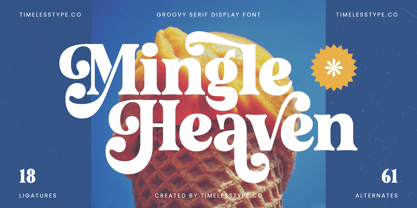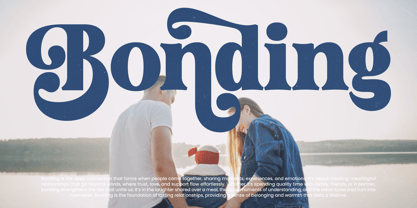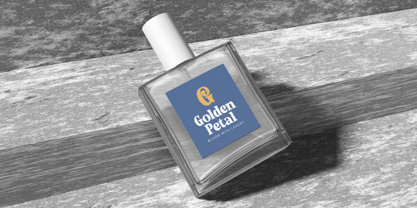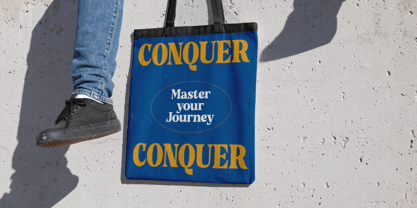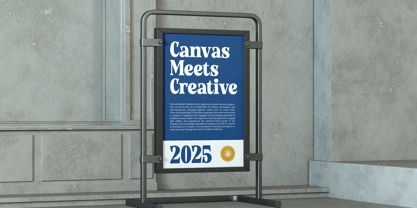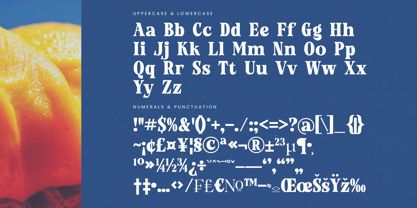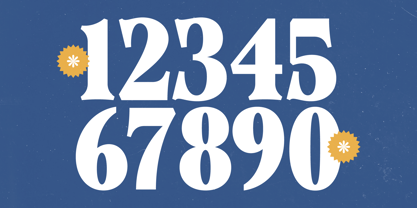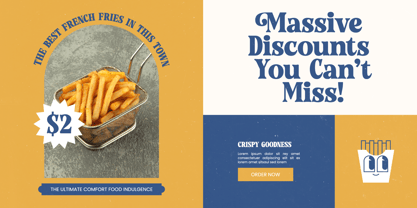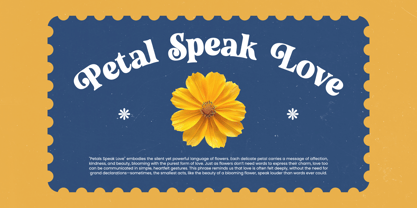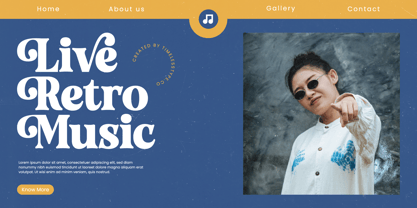
Mingle Heaven
La familia tipográfica Mingle Heaven fue diseñada por Heru Utama Putra y publicada por Timelesstype Studio. Mingle Heaven contiene 2 estilos y opciones de paquete familiar. Más información sobre esta familia
Mingle Heaven - Groovy Serif Display Font , from Timelesstype, Suitable for any projects such as: logos, branding projects, homeware designs, product packaging, mugs, quotes, posters, shopping bags, t-shirts, book covers, name card, invitation cards, greeting cards, label, photography, watermark, special events, and all your other luxury and beautiful projects that need a Luxury Serif taste.